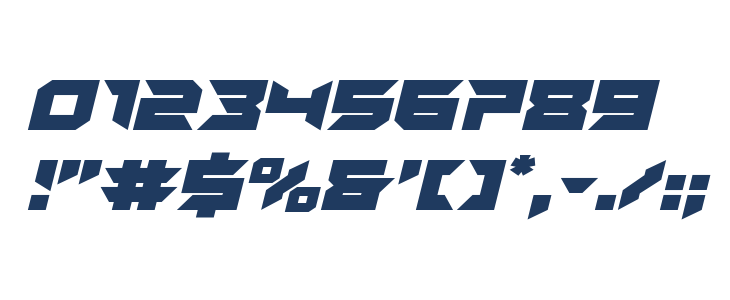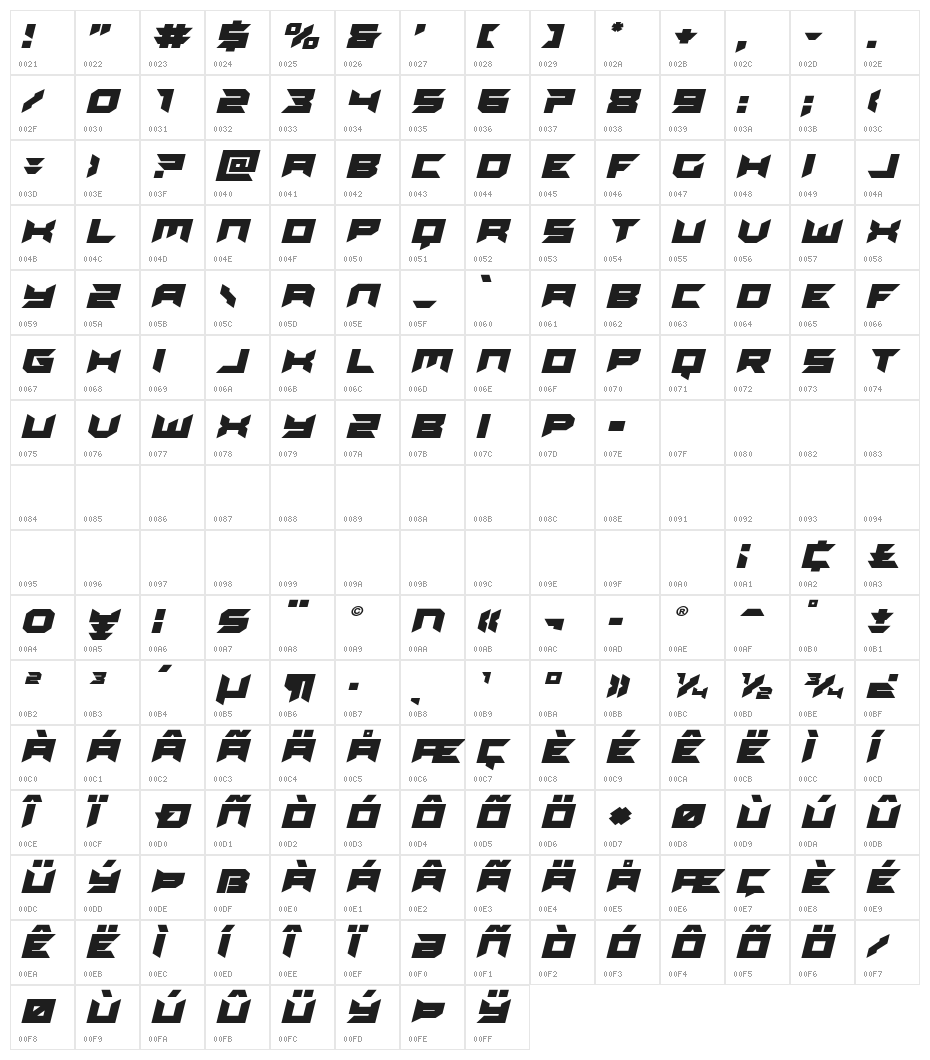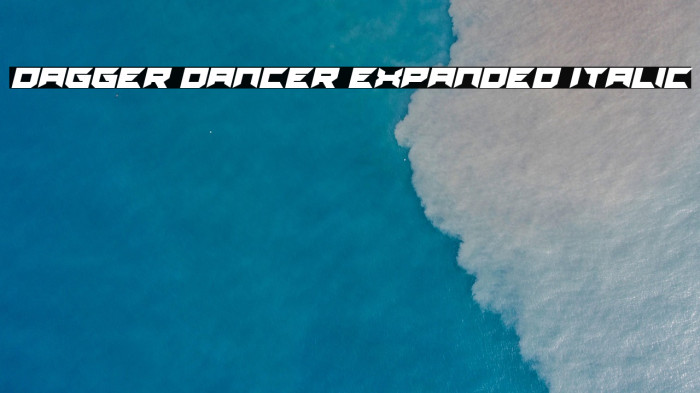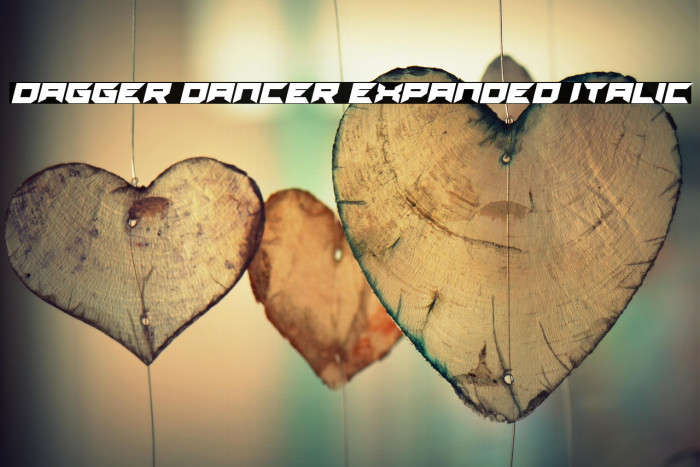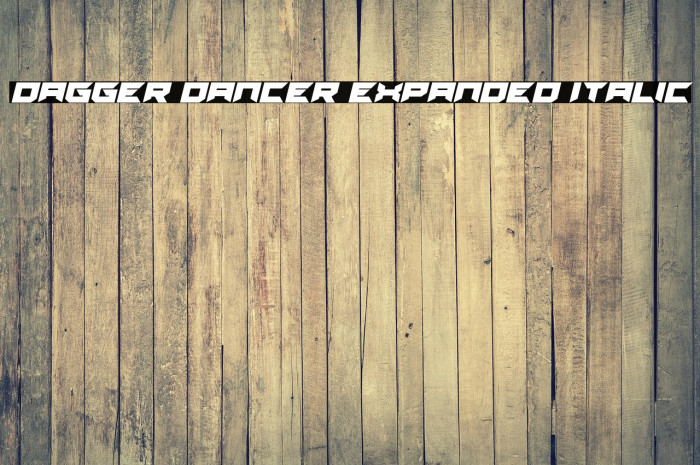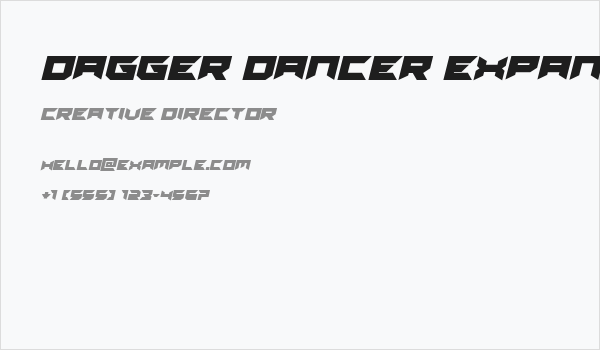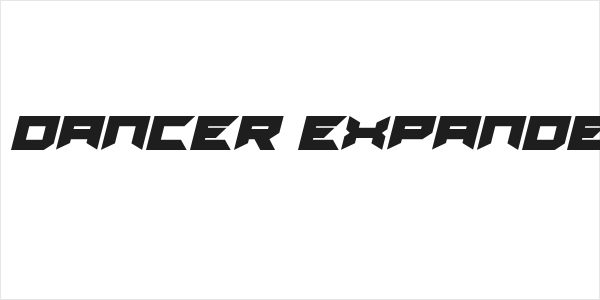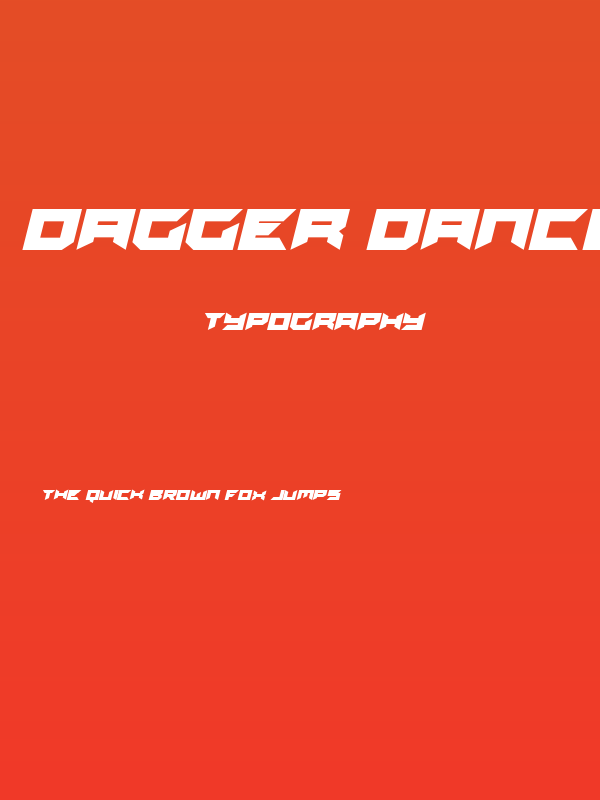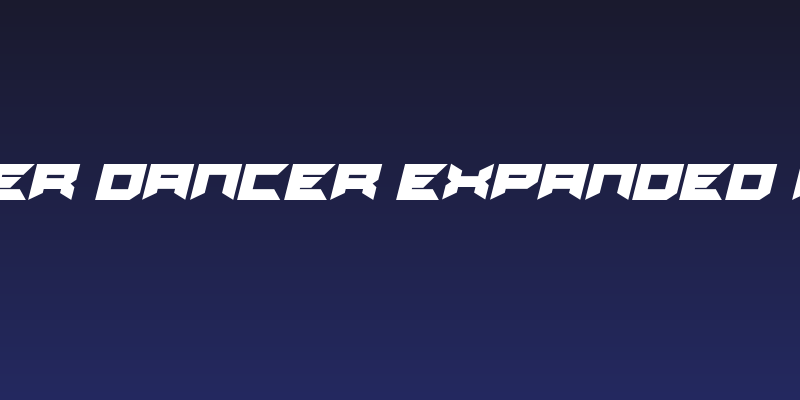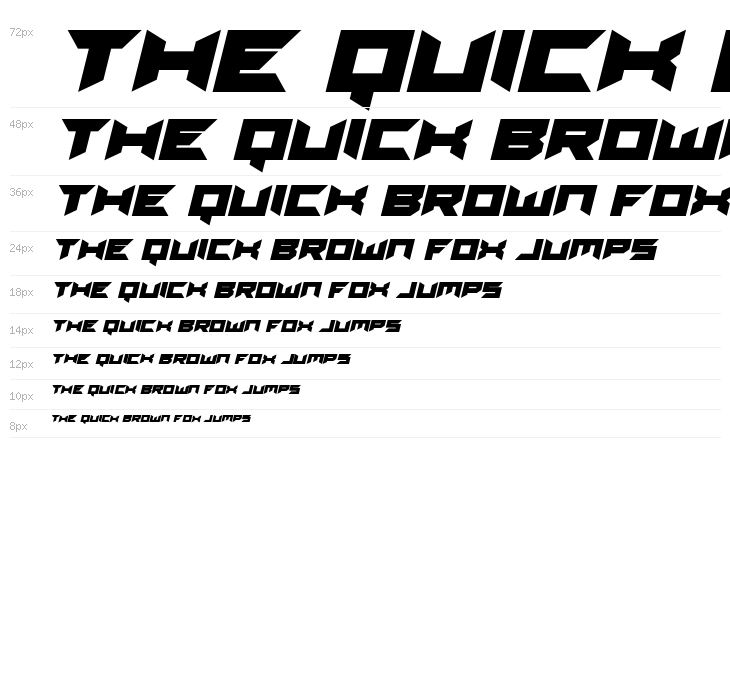
Dagger Dancer Expanded Italic Font
| Larghezza | Expanded |
| Progetti proposti | Ideal for sci-fi themed designs, video game titles, posters, and branding that requires a bold, modern look. |
Dagger Dancer Expanded Italic